Wort eintippen, Stil wählen, PNG herunterladen. Mehr ist es nicht, und es dauert etwa zehn Sekunden.
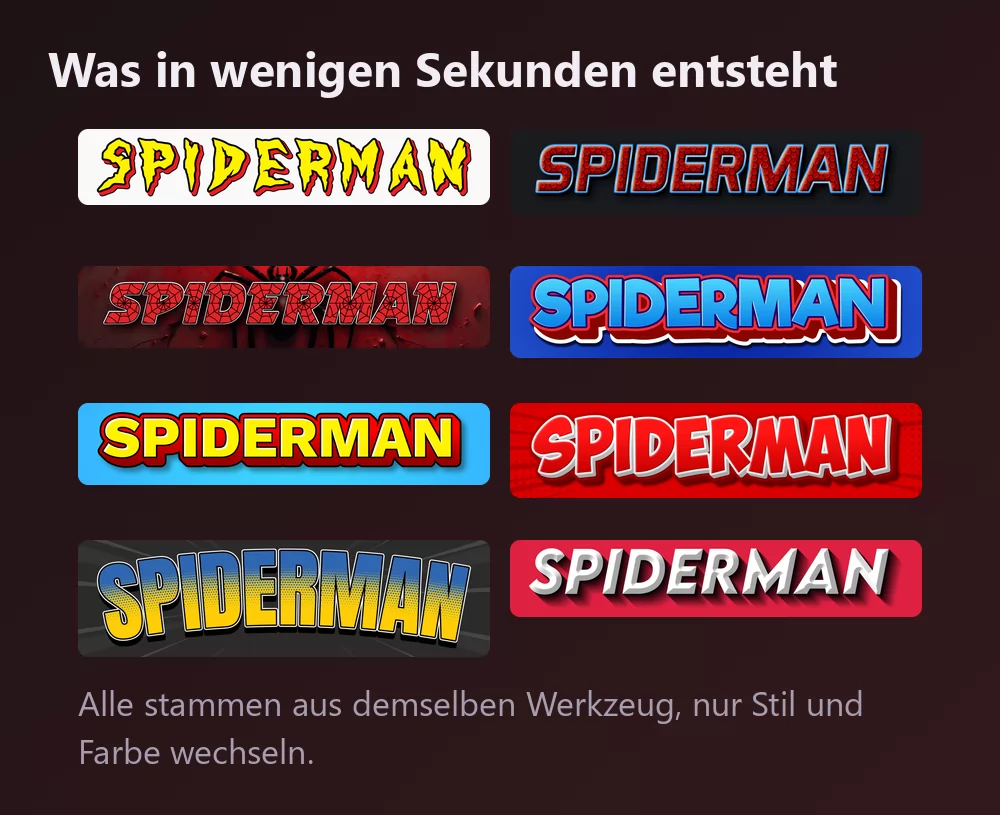
Alle stammen aus demselben Spider-Man-Schriftgenerator, nur mit einem anderen Stil aus der Liste. Nichts zu installieren, kein Konto.
Öffne den Generator und ersetze den Beispieltext durch deinen eigenen: einen Namen, einen Partytitel, einen Kanalnamen, einen Videotitel. Die Buchstaben werden beim Tippen neu gezeichnet.
Der Klassiker ist das gezackte gelbe Lettering mit dicker roter Kontur, direkt von den Comic-Covern. Im Reiter Stile lassen sich Füllung, Kontur und Schatten getrennt ändern: Die Buchstabenformen bleiben, die Farben wandern woandershin.
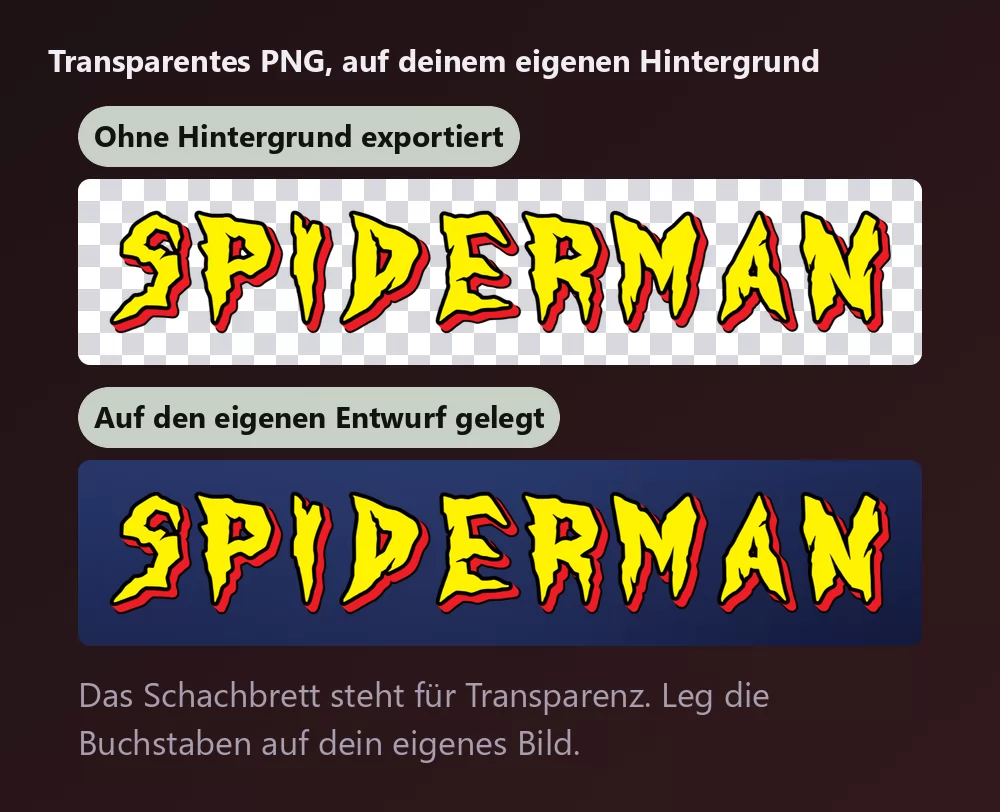
Lange Namen füllen die Breite schnell
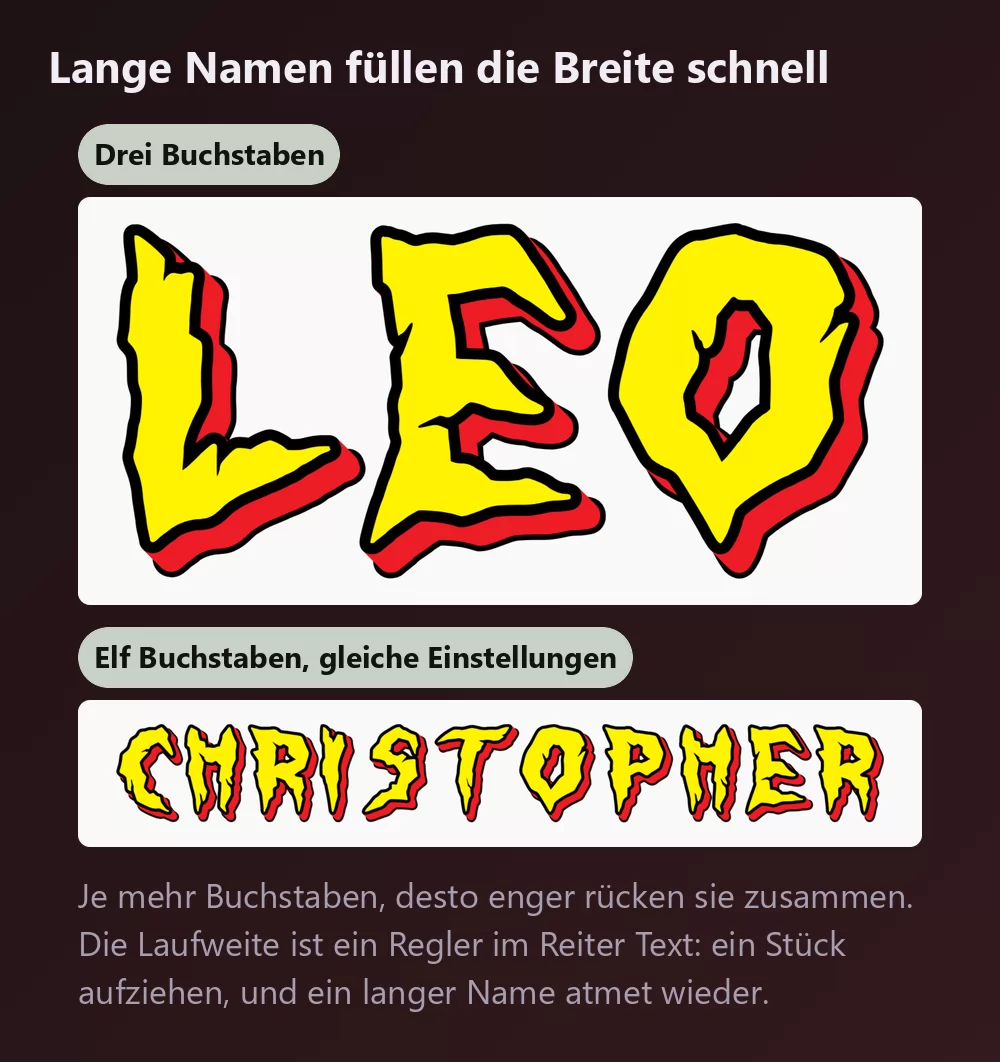
Je mehr Buchstaben, desto enger rücken sie zusammen. Die Laufweite ist ein Regler im Reiter Text: ein Stück aufziehen, und ein langer Name wirkt nicht mehr gequetscht. Im selben Reiter stecken Zoom, Zeilenabstand, Wölbung und Drehung.
Der Comic-Look oder der Film-Look
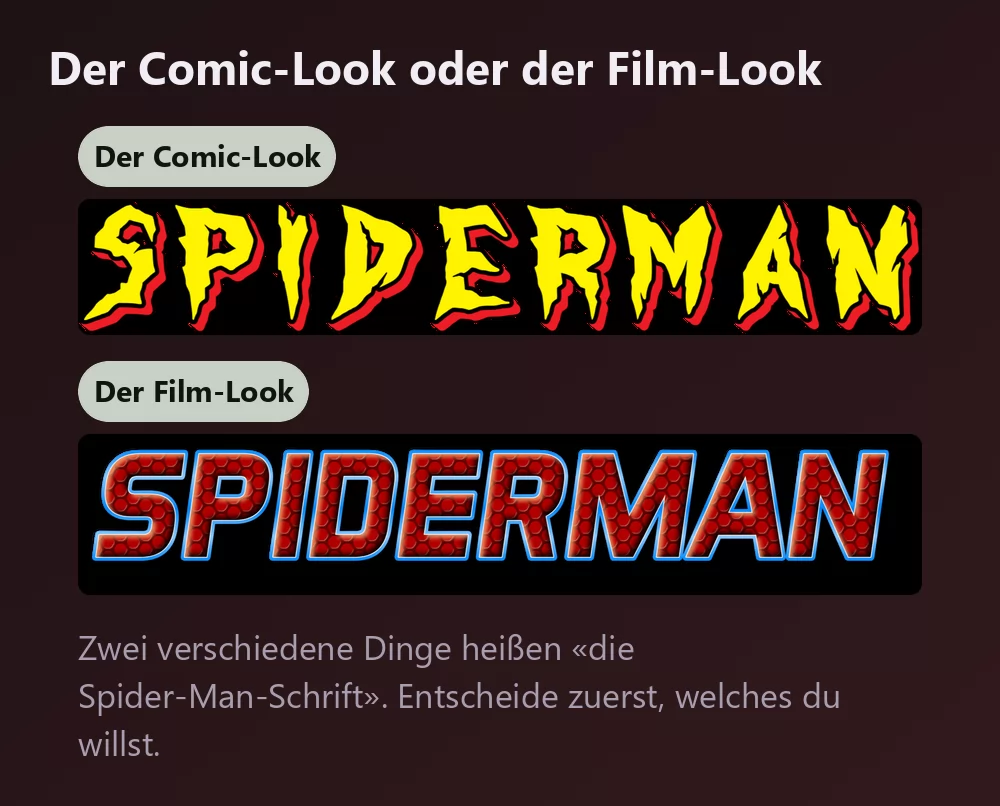
Zwei verschiedene Dinge heißen «die Spider-Man-Schrift», und es lohnt sich zu wissen, welches man sucht.
Der Comic-Look ist das gezackte gelbe Lettering mit der dicken roten Kontur, das von Jahrzehnten an Covern. Den haben die meisten im Kopf, und den liefert der Generator oben.
Der Film-Look ist glatter und dunkler: Die Buchstaben tragen die rote Netztextur mit blauer Kante, näher an den modernen Plakaten als an den Comics.
Das Netz ist der Teil, den man verstehen sollte, denn es kommt nicht von einer Schrift. Es ist eine Textur über den Buchstaben. Installiere welche Nachbildung du willst, du bekommst es trotzdem nicht: Es entsteht durch einen Effekt darüber, und genau den setzt ein Generator in einem Schritt.
Welche Schrift, wenn du eine installieren willst
Spider-Man-Text in Canva erstellen
Canva hat keine Spider-Man-Schrift in der Bibliothek, und im kostenlosen Tarif lässt sich keine installieren. Erstelle den Schriftzug als transparentes PNG und lade ihn hoch: Er landet direkt in einem Canva-Design und bleibt scharf.
Spider-Man-Text in Photoshop erstellen
Installiere eine Nachbildung, tippe deinen Text und baue die Behandlung mit Ebenenstilen nach:
- Farbüberlagerung im kräftigen Gelb.
- Kontur, auf Außen, in sattem Rot, dick.
- Schlagschatten, eng und dunkel.
- Für den Film-Look stattdessen eine Musterüberlagerung mit einer Netztextur, in den Text maskiert, plus eine dünne blaue Kontur.
Das Netz ist der Schritt, der Zeit kostet. Ein Netzmuster muss den Buchstaben folgen statt dahinter zu liegen, also maskierst du die Texturebene in den Text und verschiebst sie, bis die Fäden dort landen, wo das Auge sie erwartet.
Spider-Man-Text in Word erstellen
Installiere die Schrift, tippe deinen Text und nutze die Texteffekte für Kontur und Schatten. Word kann Text nicht mit einer Textur füllen, das Netz ist dort also nicht zu haben. Für alles, was gedruckt oder veröffentlicht wird, sieht ein exportiertes PNG besser aus.
Wie bekomme ich einen transparenten Hintergrund? Wähle im Reiter Herunterladen das transparente PNG und leg die Buchstaben auf dein eigenes Bild.
Warum sieht mein Text dem Plakat gar nicht ähnlich? Meist liegt es am Netz und an der Kontur, nicht an den Buchstabenformen. Diese beiden leisten mehr als die Wahl der Schrift.